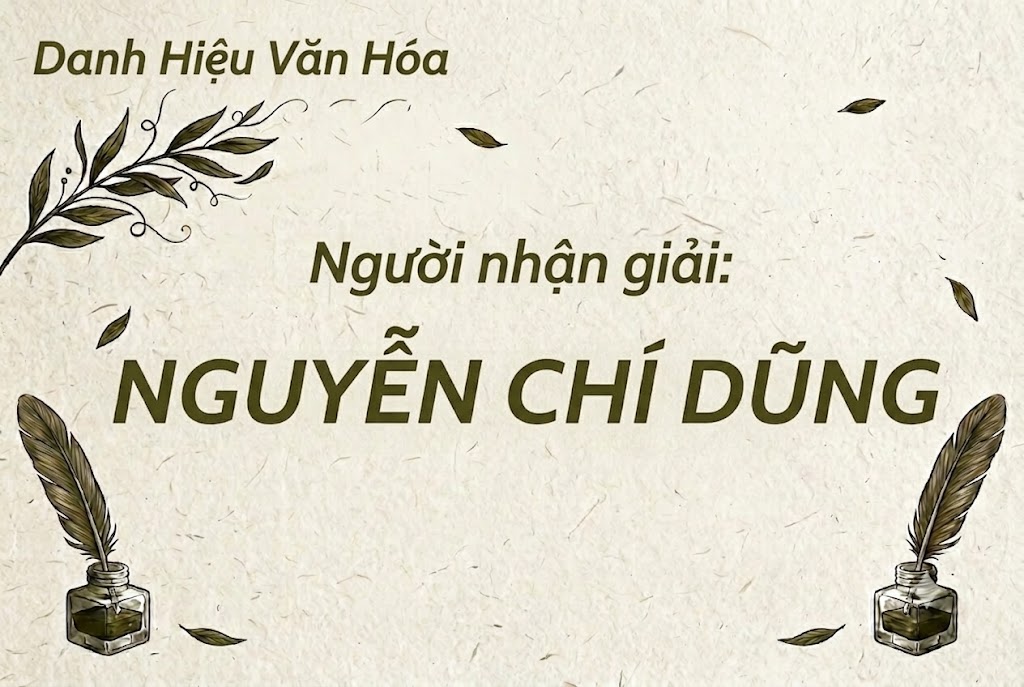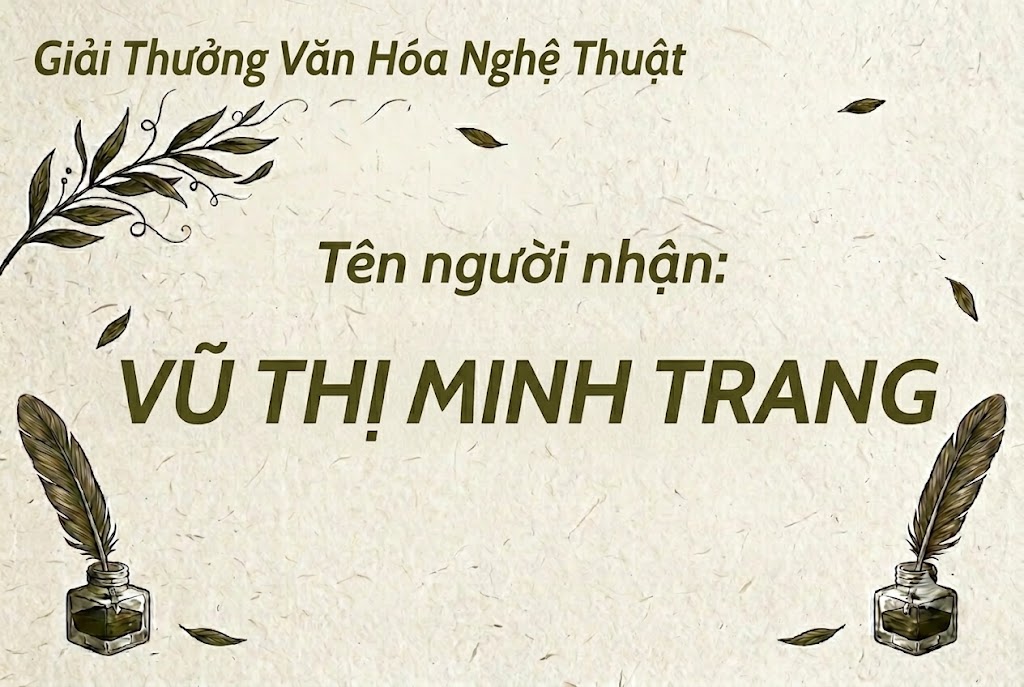
1FTV HF Gesco
Trong xu hướng tối giản và hiện đại hóa giao diện số hiện nay, các phông chữ không chân (sans-serif) dáng đứng luôn đóng vai trò cốt lõi.
Một kiểu chữ sạch sẽ, rõ ràng và có độ hoàn thiện cao sẽ giúp tối ưu hóa trải nghiệm đọc của người dùng trên mọi thiết bị di động và máy tính.
Nếu bạn đang tìm kiếm một bộ chữ đa năng để làm giao diện truyền thông, thiết kế ấn phẩm hay làm phụ đề video ngắn, thì font 1FTV HF Gesco chính là câu trả lời lý tưởng.
Giới thiệu về font 1FTV HF Gesco
Font 1FTV HF Gesco là một bộ chữ thuộc thể loại display và văn bản không chân mang phong cách tối giản, hiện đại và vô cùng thực tế.
Tác phẩm này được hoàn thiện đồng bộ ở phiên bản 1.000, đem lại sự nhất quán tuyệt đối trong từng đường nét của hệ thống ký tự hoa và thường.
Nhờ các thông số kĩ thuật tối ưu này, phông chữ có khả năng hiển thị sắc nét, giúp bạn tự tin ứng dụng trên nhiều hệ thống phần mềm đồ họa khác nhau.
Đặc điểm nổi bật của phong cách thiết kế HF Gesco
Sức hút lớn nhất của font 1FTV HF Gesco đến từ cấu trúc hình học cân đối và phom dáng đứng vô cùng ngay ngắn, thanh lịch.
Kiểu chữ này không quá cầu kỳ hay phá cách, mà tập trung hoàn toàn vào sự tinh tế, tạo cảm giác chuyên nghiệp và đáng tin cậy cho người xem.
Bộ font hỗ trợ trọn vẹn cả hệ thống chữ cái thường bên cạnh hệ thống chữ viết hoa, tạo điều kiện thuận lợi cho việc phân tách các tầng nội dung văn bản.
Khoảng trống bên trong và các nét chữ được tính toán tỷ lệ vô cùng khoa học, giúp văn bản luôn rõ ràng và không bị dính nét khi thu nhỏ bố cục.
Để phông chữ vận hành mượt mà trên mọi hệ thống máy tính, phiên bản font 1FTV HF Gesco đã trải qua quy trình xử lý thông số kĩ thuật kỹ lưỡng.
Hệ thống khoảng cách chữ (kerning) và độ giãn dòng (tracking) đã được căn chỉnh chuẩn xác, giúp các từ khi đứng cạnh nhau luôn giữ được khoảng trống thẩm mỹ tốt nhất.
Bên cạnh hệ thống chữ cái hoa và thường đồng bộ, phông chữ còn tích hợp đầy đủ dãy số từ 0-9 cùng hệ thống các ký tự đặc biệt, dấu câu thông dụng (1234567890.:,;'"(!?)+-*/=).
Tiện ích này giúp bạn thoải mái sáng tạo các nội dung quảng cáo hay biên tập video tiếng Việt mà không lo gặp phải tình trạng lỗi hiển thị.
Hình ảnh demo thực tế của font 1FTV HF Gesco
Để giúp bạn dễ dàng hình dung khả năng co giãn và hiển thị linh hoạt của phông chữ này trên các kích thước khác nhau, hãy cùng xem qua bảng mô phỏng thực tế:
Kích thước nhỏ (12pt – 24pt): Các nét chữ đứng và bộ chữ thường vẫn hiển thị rất rõ ràng, ngay ngắn, cực kỳ dễ đọc trên màn hình điện thoại di động.
Kích thước lớn (36pt – 72pt): Đây là không gian lý tưởng để font chữ phô diễn toàn bộ sự chuyên nghiệp, tạo hiệu ứng thị giác gọn gàng cho các tiêu đề chính.
Ứng dụng của font HF Gesco trong thiết kế đồ họa và làm video
Sở hữu nét cá tính tối giản và cấu trúc hoa – thường linh hoạt, font 1FTV HF Gesco mở ra không gian ứng dụng rộng lớn cho các dự án truyền thông:
Thiết kế ảnh thu nhỏ mạng xã hội: Đây là lựa chọn tuyệt vời cho các chủ đề về giáo dục, chia sẻ kiến thức, vlog đời sống hoặc công nghệ để tăng tính chuyên nghiệp và độ tin cậy.
Làm phụ đề cho video ngắn: Kiểu chữ đứng thanh thoát này rất thích hợp để làm phụ đề (subtitle) chạy chữ cho video Tiktok, Reels, giúp người xem dễ dàng theo dõi nội dung.
Banner và poster quảng cáo doanh nghiệp: Hoàn hảo cho các poster giới thiệu sản phẩm, banner chương trình ưu đãi hoặc các ấn phẩm truyền thông đòi hỏi sự gọn gàng, súc tích.
Nhận diện thương hiệu phong cách tối giản: Phù hợp làm logo dạng chữ, biểu ngữ hoặc thiết kế nhãn mác cho các thương hiệu thời trang, mỹ phẩm hoặc các công ty dịch vụ hiện đại.